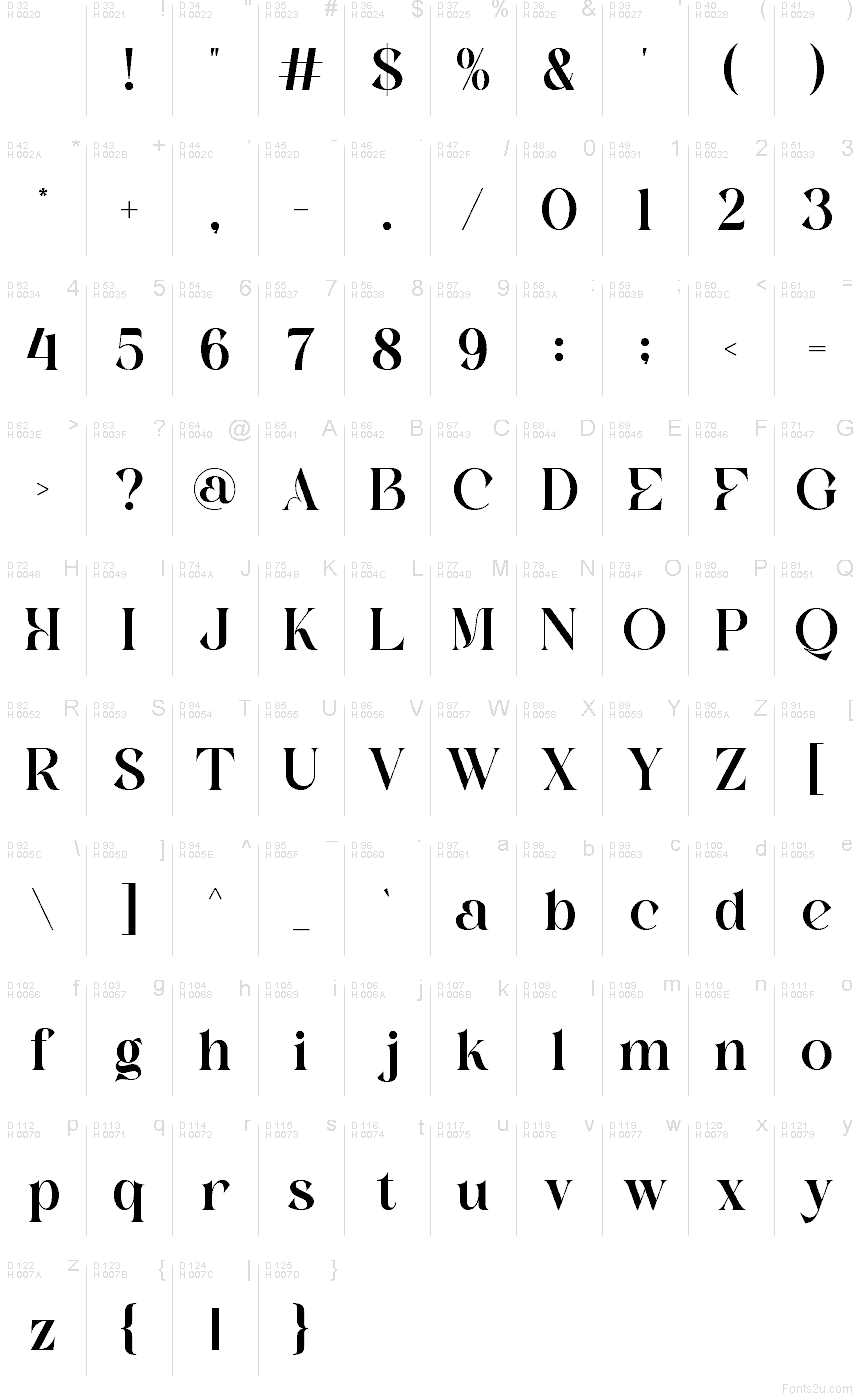
خط Basera من Ermedia Studio هو خط تزييني مجاني ذو زوائد، يتميز بتباين حاد للغاية بين الخطوط السميكة والرفيعة وبأشكال حروف عريضة ذات طابع نحتي. وتُضفي الانحناءات العميقة والوصلات الدقيقة كالإبر والقطوع الحادة على الخطوط مظهرًا يبدو وكأنه مطوي أو منحوت، مما يمنح الحروف المألوفة مظهرًا دراميًا غير معتاد.
يناسب طابعه التحريري المستوحى من عالم الموضة الراقية ترويسات المجلات وتغليف العطور، لا سيما في مشاريع الجمال والثقافة القائمة على الخطوط التعبيرية. كما يمنح التباين الواضح هوية العلامات التجارية الراقية طابعًا راقيًا وغير تقليدي، بفضل أشكال فريدة بما يكفي لتعمل وكأنها شعار صُمم خصيصًا. وإلى جانب عالم الموضة، يمكنه إضفاء لمسة درامية تجمع بين طابع العصور القديمة والمعاصرة على أغلفة ألبومات الموسيقى التجريبية وملصقات الفعاليات الفنية.